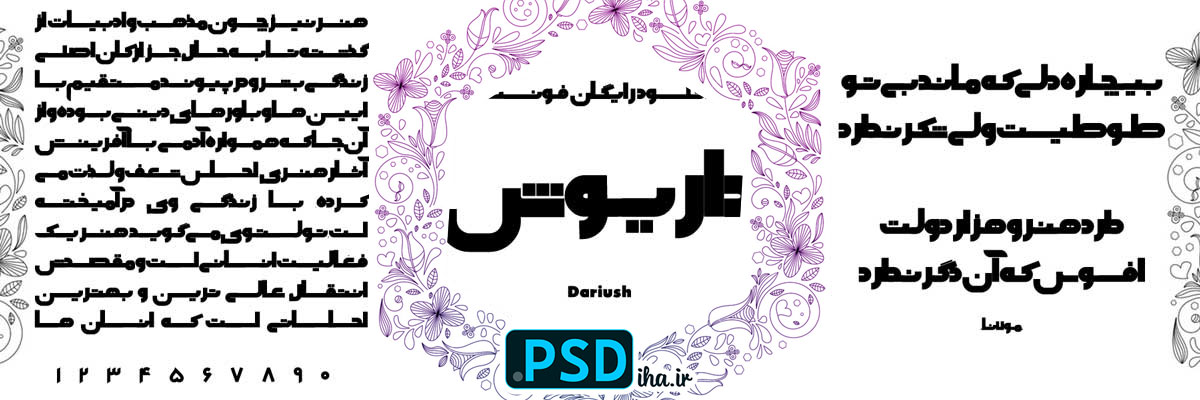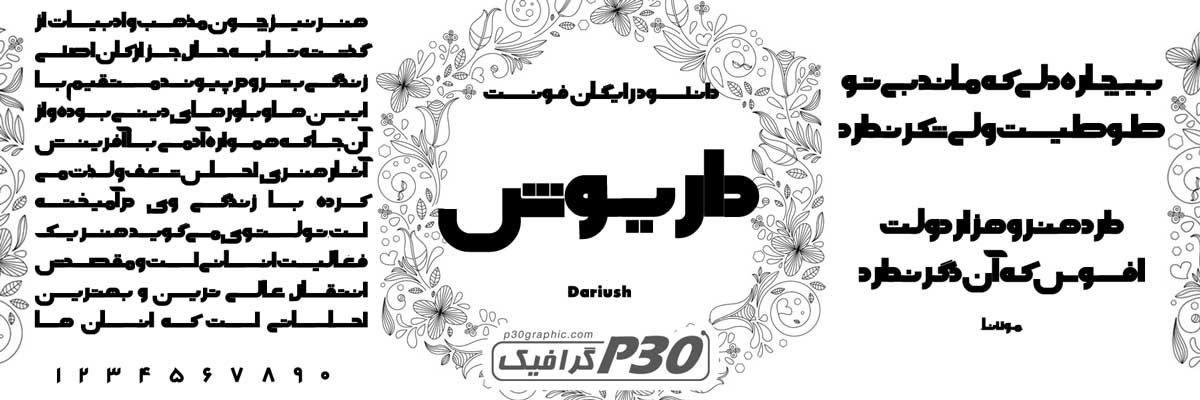
فونت داریوش
اگه عاشق فونت‌هایی هستید که هم آشنا باشن و هم یه حس تازه بدن، فونت داریوش رو از دست ندین. من خودم تو پروژه‌های چاپی‌م، از لوگوهای تلویزیونی‌وار گرفته تا تراکت‌های تبلیغاتی، بارها سراغ این فونت فارسی رفتم و هر بار مشتری‌ها می‌گفتن “این دیگه چقدر شیک و امروزیه!” ایده‌برداری‌ش مستقیم از لوگوی برنامه محبوب “عصر جدید” اومده، با اون خطوط نرم و مدرن‌ش که انگار از آینده می‌گه. به خاطر شباهت‌ش به فونت‌های پرطرفدار مثل لوک و عمر، طراحان و گرافیست‌ها عاشق‌ش شدن – تصور کنید تیتر یه پوستر تلویزیونی یا کارت ویزیت یه استودیو با داریوش؛ مخاطب‌ها فوری حس حرفه‌ای‌گری و جذابیت می‌گیرن!
چرا فونت داریوش انتخاب طراحان چاپیه؟
این فونت فارسی، با طراحی الهام‌گرفته از عصر جدید، تو پروژه‌های گرافیکی مثل کارت‌های ویزیت، تراکت‌های تبلیغاتی، لیبل‌های محصولات و حتی پوسترهای رسانه‌ای می‌درخشه. خوانایی‌ش تو اندازه‌های مختلف عالیه و با نرم‌افزارهایی مثل فتوشاپ یا ایلاستریتور، بدون هیچ مشکلی رندر می‌شه. شباهت‌ش به لوک و عمر، یه حس نوستالژیک مدرن می‌ده، اما با لبه‌های تیزتر برای چاپ‌های حرفه‌ای. یادمه یه پروژه برای یه کانال یوتیوب داشتم؛ با داریوش، لوگو رو طراحی کردم و چاپ روی بنرها انقدر واضح و جذاب بود که بازدیدها دو برابر شد. حالا دیگه تو هر طرحی که بوی رسانه و خلاقیت بده، اول به این فونت فکر می‌کنم!
فونت داریوش، با خطوط نرم و الهام‌گرفته از لوگوی عصر جدید، همه نیازهای طراحان رو پوشش می‌ده. وزن متعادل‌ش برای تیترها و متن‌های اصلی مناسبه. انحناهای ظریف‌ش، جذابیت بصری می‌ده بدون اینکه شلوغ بشه. با فونت‌های محبوب مثل لوک و عمر جور درمیاد و برای ترکیب‌های خلاقانه عالیه. اگه می‌خواید طرح‌هاتون مثل یه برنامه تلویزیونی پربیننده بشن، این فونت کلید موفقیته!